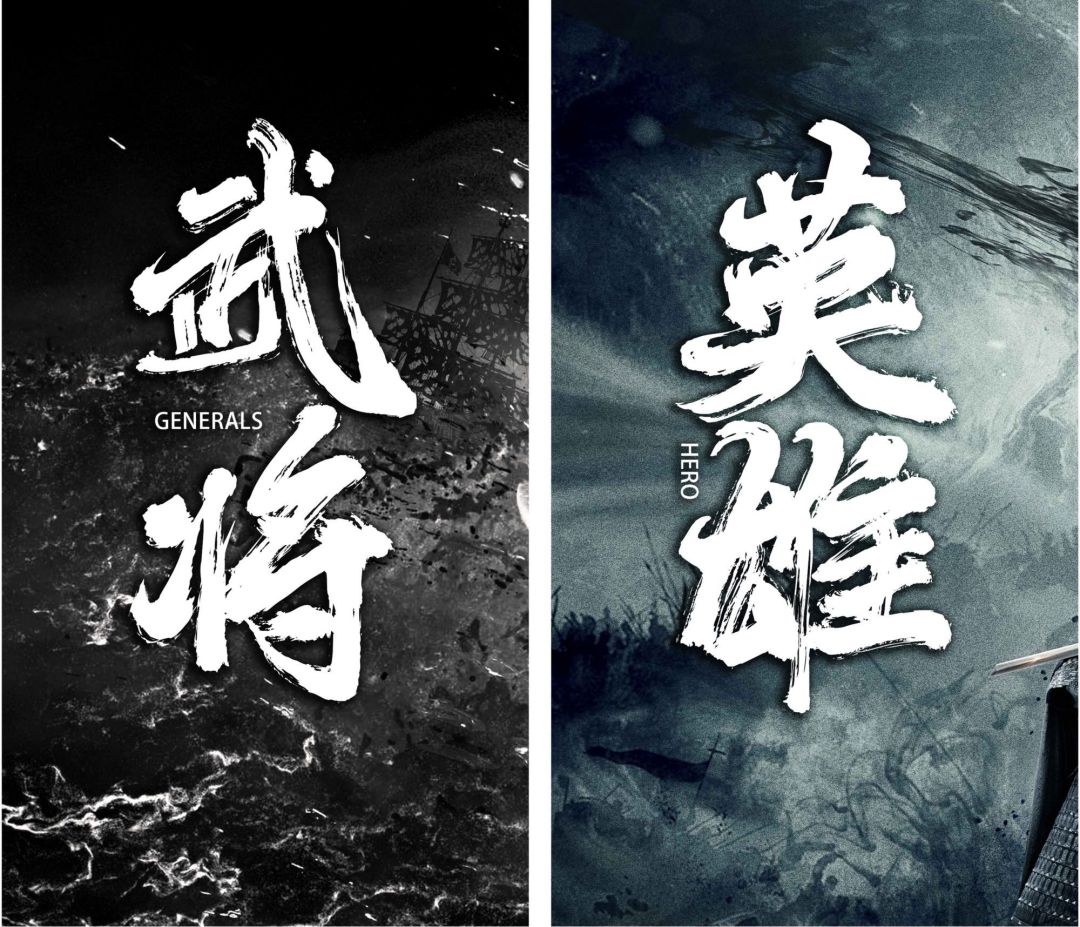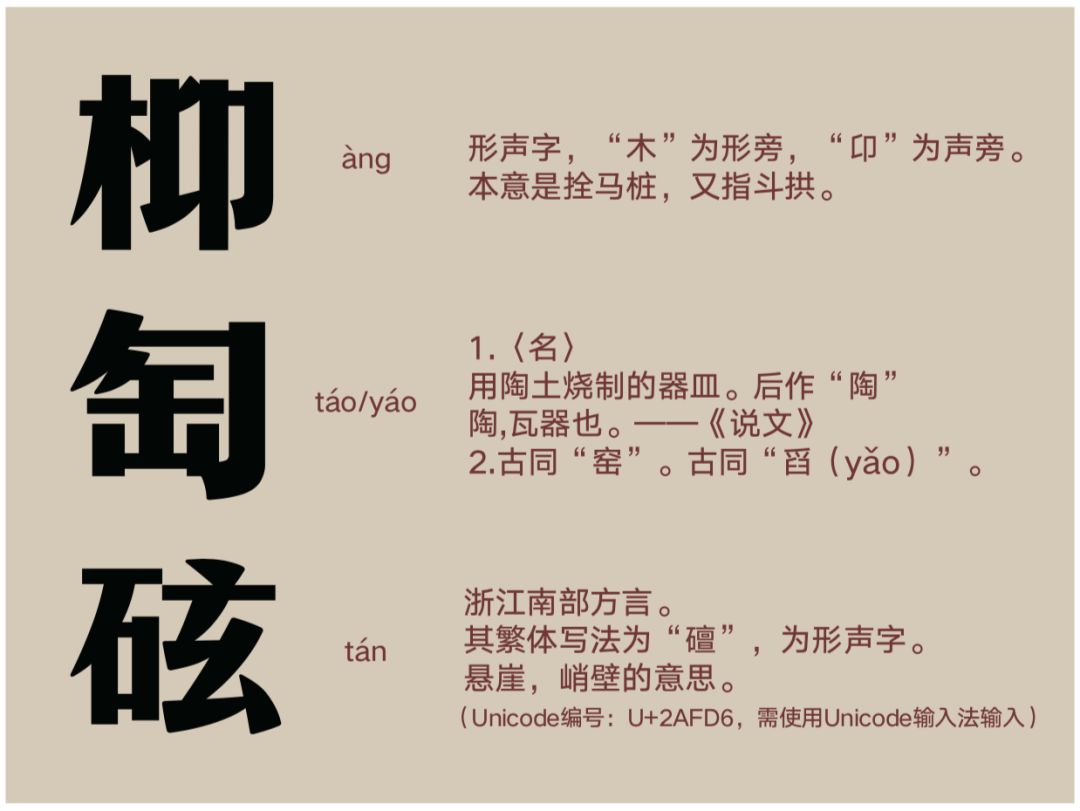
字由发布年度字体,2020年最有影响力的都在这了
虽然是今年刚冒尖的年轻字库品牌,但点字库已经上新了21款字体,其中一款极具几何特征的男性化标题字最为耀眼,它就是点字倔强黑。
作者卢鑫亚在设计之初,就想传达给人一种果敢和进取的情感,通过几何化笔形的特殊处理,让字形刚劲有力,棱角分明,再搭配简洁明朗的线条,使顿挫之间有一种韵律之感。适用于大标题、品牌广告等需要强视觉表现的环境,自带“power bgm” 。
今年很多字库公司都推出了以美食命名的字体,比如喜鹊乌冬面体、字体视界法棍体,还有文悦孙小松鲷鱼烧体。
它最大的特点,就是字形圆润活泼,粗细对比明显,给人一种很温暖的感觉,当然应用于报菜名,更是不在话下。
2019 阿里巴巴 UCAN 设计大会上,一款以“普惠”之名诞生的字体,免费开放商业版权。中文部分由汉仪字库主创设计师陶一泓主导,共收录了 116,895 个全形汉字,西文部分由 Monotype 字体总监小林章主导, 共 7,205 个拉丁字母,覆盖 172 个语种。
整套字体的设计历时 10 个月,不仅包含突显企业品牌个性的标题字,还囊括了更为实用的内文字,兼顾多个场景下的应用……
今年,可口可乐携手“好字在”,共同设计了一套字体——“在乎体”,以在乎为灵感,以文字为表达。并呈现了一场让人“悦目”的文字艺术展,借由一笔一划,表达圆融、力量、担当、从容、变化。
继阿里巴巴普惠体后,oppo又官宣了一款授权全社会免费使用的字体,它包含226003个字符,5个家族Light / Regular / Medium / Bold / Heavy 。覆盖21个国家语言、11个语种,中文部分由汉仪字库字体设计总监朱志伟指导,字体设计师黄珍元设计完成,西文部分则由美国Pentagram五角公司设计,汉仪字库西文项目组协作完成。字体采用全新骨架,中宫自然舒适,奉行简洁真实,把握更多细节,并针对移动端进行了像素级优化。
随着技术的革新,字体设计进入了一个可以无限制变化的新纪元。正如小米和方正联合推出的MIUI动态字体系统,获得了2019红点奖。
它是将几个字体紧凑地封装在单个字体文件中,通过定义字体内的变化,来实现单轴或者多轴设计空间。用户只要拖动相应滑块,即可改变字体大小和字重粗细,让阅读体验更为极致。青年手写人秦川,热衷于书写,擅长将笔墨与设计结合。第一款手书“汉仪秦川飞影”发布后,非常受设计师欢迎,因而又推出凝练洒脱的汉仪秦川漫书。
“漫”意为随意,没有限制,没有约束,“漫书”即随意书写。 所以这款字具有强烈的个人风格,笔触细节丰富,可以广泛应用于多种场景。
方正不孤独体是以北大医疗脑健康儿童发展中心,孤独症儿童的书写作品为基础,在方正电子、方正手迹的技术支持下,开发的第一款孤独症儿童参与创作的公益字体。
它的诞生,让我们看到了孤独症儿童并没有放弃与世界的沟通,更多的是以书写或绘画的方式来触摸世界的温度。同时也呼吁全社会,给予他们更多的包容与鼓励,让“星星的孩子”不再孤独。
上榜理由: 37年来,Helvetica首个新字体今年最大的新闻就是蒙纳(Monotype)于4月推出的Helvetica Now。近4万个字母、数字、标点符号被重新绘制,还解决了当显示或微字体时,可读性会随着字体的放大和缩小的问题,扩大了其外观和实用性,更易阅读。
字体设计大师马修·卡特(Matthew Carter)四年前收到森泽公司的邀请,来日本制作西文字体,其目的有二:一方面为了增加字库中的西文产品,另一方面也为了提升日文字体排印领域对西文的认识。合作的成果便是超级字体家族 Role,包含衬线体、无衬线体、方衬线体和圆体,最多包含九个字重以及意大利斜体。
值得一提的是,这一作品是由卡特主导设计概念,但具体的制作,是他指导森泽的字体设计师樽野樱、中野正太郎、冈野邦彦、半田蓝、以及小针优弥完成的。对于设计师和字体公司来说,这具有很大的教育意义。另外,森泽发行字体时从不注明具体设计师的名字,而卡特则特别要求所有的宣传和字体样张中都必须注明。
虽然现在庞大的字体家族往往与插值变换、可变字体等最新技术联系在一起,但 Role 在不同风格和字重之间的变化,并非完全是线性的,虽然出自同样的概念和骨架,但希望能在不同情况下,传达准确的情感和声音。
逆反差字体是拉丁文字设计所延伸出来的概念,主要是利用逆反差效果所造成的奇异性格 (quirky personality) 来引起注意力。
台湾设计师廖恬敏(Tien-Min Liao)设计的Ribaasu,就是这样一款包含了CJK字符的逆反差字体(Reverse Contrast)。不仅荣获了日本森泽字体设计大赛铜奖,还斩获了纽约字体俱乐部的评审特选奖。
书法体大家都很喜欢用,但真正可供免费商用的还没有,庞门正道出的这一款就是,应用范围相当广。
由资深门友车港敏手写数月,并由庞门正道出资制作,总耗时9个月,共计6000多个汉字,目前只支持简体。
问藏书房是造字工房创始人丁一,为了让更多对审美有需求的朋友,免费借阅艺术类书籍而创建,同时精心打造了一款“问藏书房”的字体,并开源给中国大陆地区一切个人与商业机构免费使用。
字体现代简约,中宫紧凑,视觉阅读极具层次感。字符编码采用中华人民共和国GB2312-80字符集标准,按需添加101个汉字。共收容字数6864CJK汉字,ASCII常用字符100个。
今年年初,在东京国立博物馆开幕的颜真卿特展,堪称近十几年里,最高水平的中国书法展览了。颜楷是民族文化的瑰宝,本着对先辈的敬畏之心,汉仪字库从1997年开始,就着手对颜真卿书法的研究与再设计。从《多宝塔碑》、《颜勤礼碑》,到《颜家庙》、《麻姑仙坛记》,将340余字的字帖,融入字库,再历经20余年,三代设计师精心打磨,最终完成了国标简繁9169字符集——汉仪颜楷。
经汉仪字库艺术顾问、著名字体设计师朱志伟指导,在松阳县政府的支持下完成。字体基因来自松阳的老门牌,通过再次设计改进后,字体的笔画粗细对比更加鲜明,空间结构布局更合理,再加上它笔画无饰角,字形严谨不失松快,具有良好的标牌易读性。除了9169中文简繁+当地常用字+拉丁字符,还有三个生僻字,是独属于那个时代的视觉记忆与文化表征。